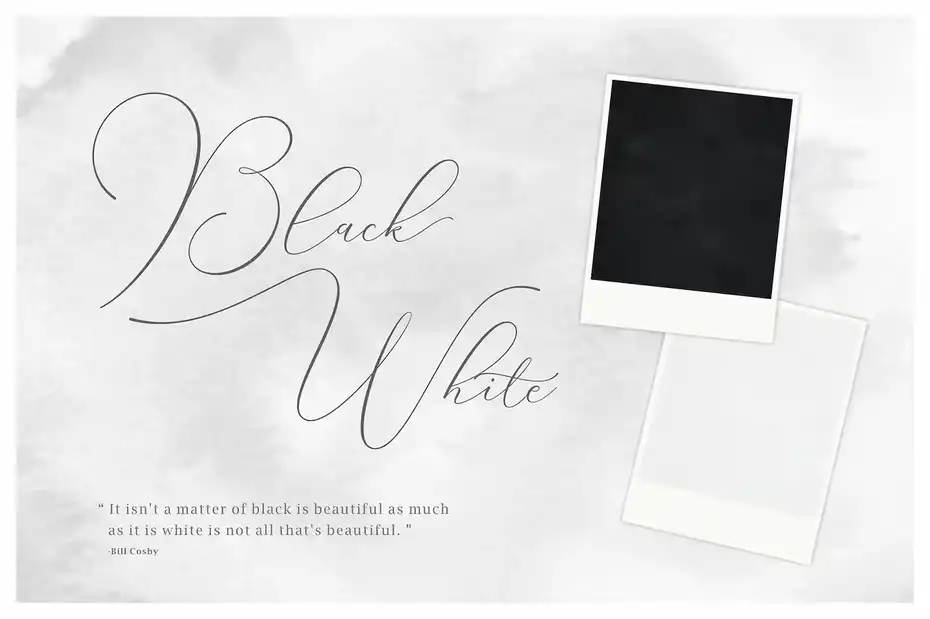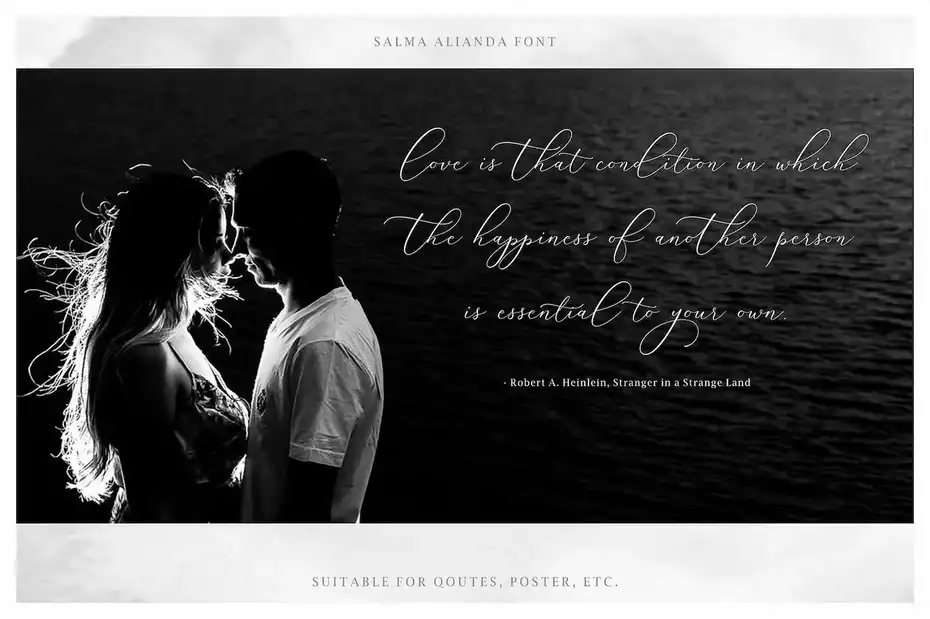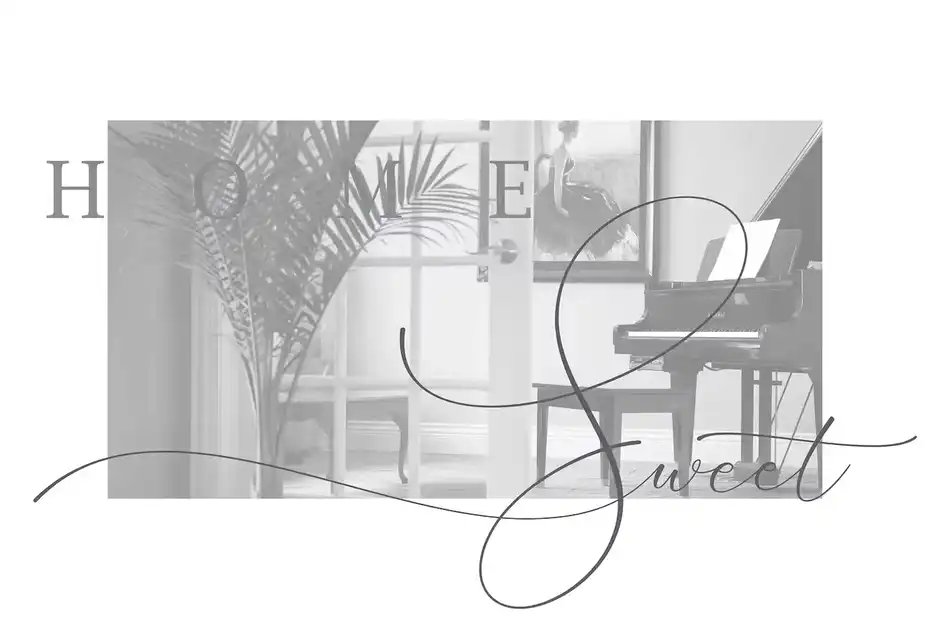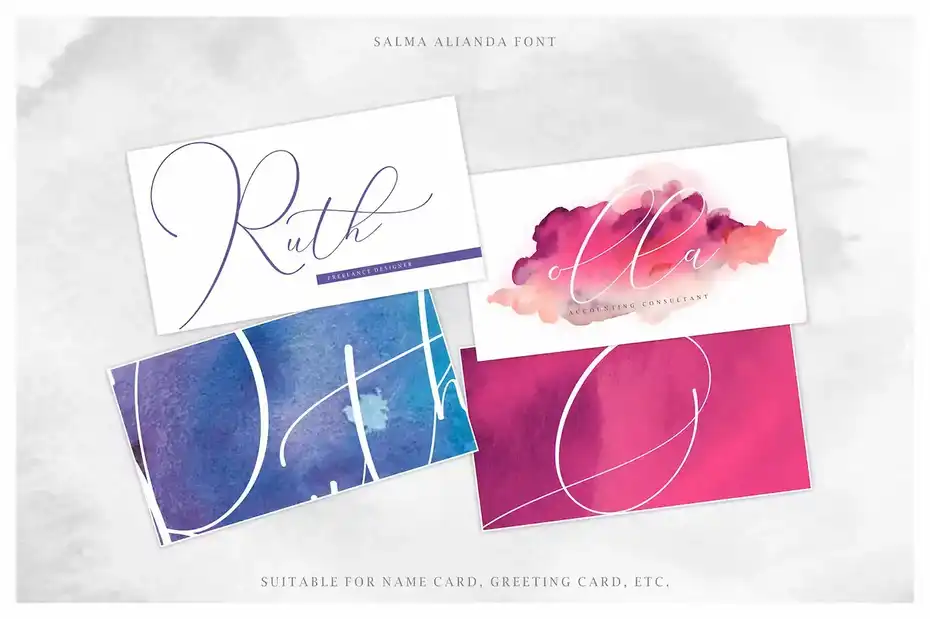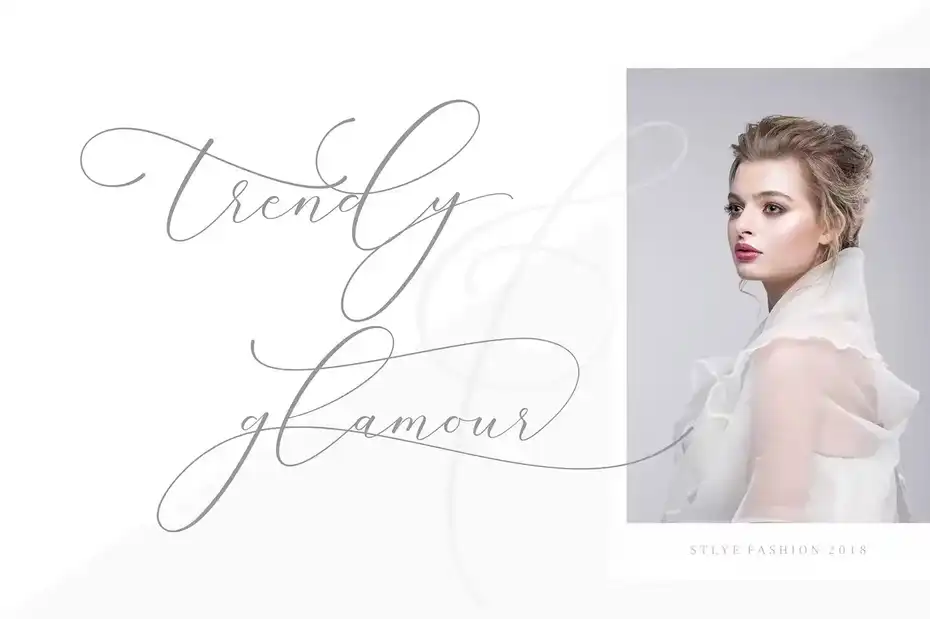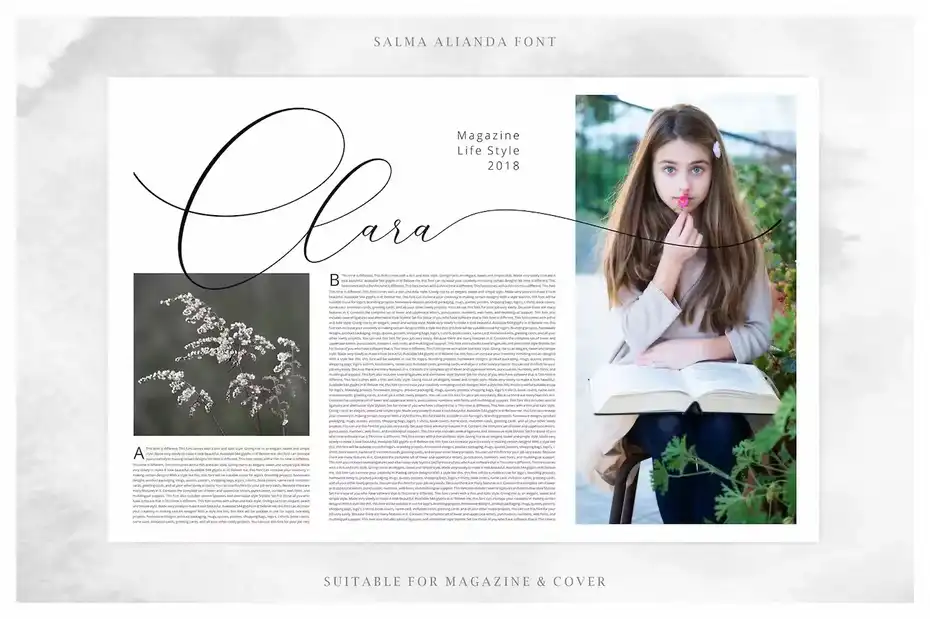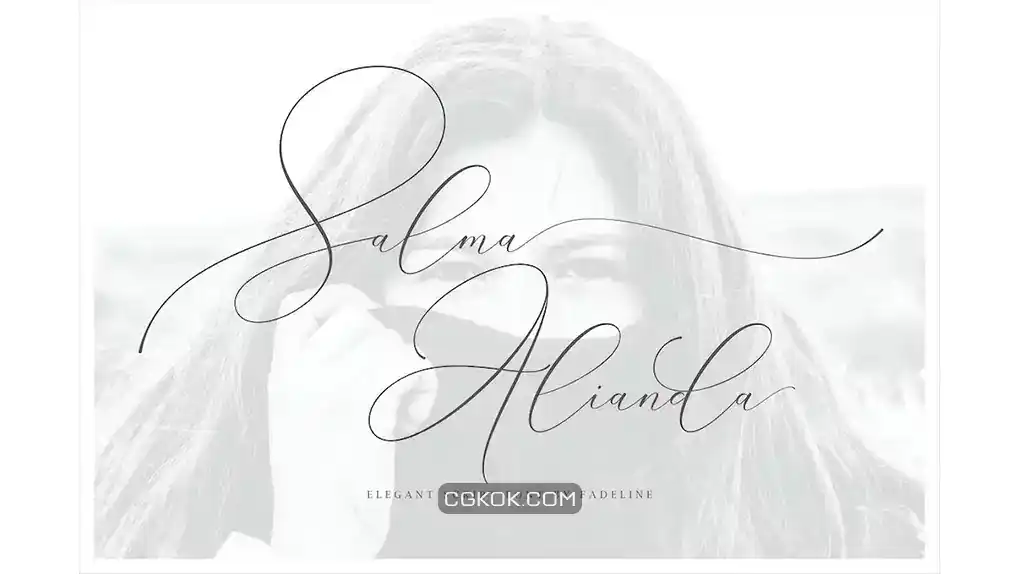
دانلود فونت انگلیسی پیوسته Salma Alianda – Elegant Font Script
فونت انگلیسی پیوسته Salma Alianda – Elegant Font Script : این مجموعه شامل یک فونت انگلیسی دست نویس است که برای لوگو، برندینگ، بسته بندی محصولات، ماگ، نقل قول، پوستر، بگ خرید، تیشرت، جلد کتاب، کارت دعوت، کارت تبریک و غیره مناسب میباشد.